拼搏,是运动员最好的竞技体育精神;夺冠,是赛场上最燃的热血梦想。
锐字潮牌字库2款限定免费商用字体【锐字奥运精神拼搏简、锐字奥运精神夺冠简】和14款潮牌字体,字敬奥运,助力媒体报道,传递拼搏精神,传达夺冠期盼!
一、扉页 - - 锐字潮牌字库:冬奥官方媒体宣传字体提供商之一
2022年北京冬奥会即将于2月4日启幕,锐字潮牌字库多款字体,正在被官方及各大媒体用于宣传海报和视频中。趣味科普、多视角解读、冰雪日记...一起来看看各大官方媒体报道中锐字的身影:
这些动态影像,让冬奥之火在冰雪中被点燃。为迎接2022年北京冬奥会,锐字潮牌·字敬奥运2款限定免费商用字体(锐字奥运精神拼搏简免费「已发布」、锐字奥运精神夺冠简免费「即将上线」)以及14款限时优惠潮牌字体,助力奥运报道,为奥运健儿加油。每一位拼搏的运动员,你们都是冠军!
二、影集 - - 16款字体传递拼搏精神,传达夺冠期盼
在一众冬奥影像中,字体成为优秀视觉效果呈现的重要因素。我们用16款字体,制作了一本冬奥字体影像集,传递奥运健儿拼搏精神,并为他们送上祝福,期待他们续写奋勇夺冠的辉煌。
(1)拼搏篇·为冰雪之梦而战
△ 锐字奥运精神拼搏简免费|字体倾斜,呈现向前飞奔的姿态,气势十足;笔画干脆利落,具有力量感。本字体提供在奥运、亚运或体育行业、体育报道中免费商用。
△ 锐字工房澎湃简 | 一款醒目粗犷的宋体字,笔画配合三角形装饰,感觉澎湃激情的冰上竞速一触即发!
△ 锐字工房锋芒黑简|极具艺术感的扁平黑体,简洁大方,致敬正在拼搏的运动员们!△ 锐字洪荒之力简 特黑|设计灵感来源于奥运运动员的采访语录 "洪荒之力" ,旨在体现原始、粗野的生命活力感。
△龙书慢生活简 阳光|字体设计旨在表达 "慢生活" 理念,场上比拼竞技速度,场下却需要慢慢等待。相信你们终究阳光会拨开阴霾,在场上一展雄风。
△ 海派腔调清夏简|冬日的冰雪,却有夏日的激情。通过这款清秀的字体,让我们一起感受冰雪的温度,让胜利如花绽放。
△ 龙书势如破竹简|笔触较为粗实,字体清晰,超有力量,每个运动员的胸中都燃烧着一团火焰,以势如破竹的气势迎接对手,两军相遇勇者胜!
△ 海派腔调禅粗黑简|字体错落有致,富于变化,洋溢着情怀,如一颗颗炽热的赤子之心,昭示着对冰雪运动的热爱,热爱可抵岁月漫长!
△海派腔调滚石黑简 超黑|拥有未来感的城市字体,与 "一起向未来" 的口号不谋而合,我们与世界携手共进,走向未来。
(2)夺冠篇·期待奥运健儿凯旋
△ 锐字云字库小标宋简|经典宋体助力冬奥之梦!字体端正清秀,横轻竖重,结构均匀,笔法严谨,有着宋体字的典型特征。
△ 锐字云字库锐倩简|笔锋避免尖锐,设计成微小的圆弧,柔润舒畅,婉转妩媚、温顺乖巧,在平淡中蕴藏着无限力量。
△锐字云字库美黑简|字体匀称、清秀美观,端正又正气。我们的每一位运动员,都是如此之 "美" !
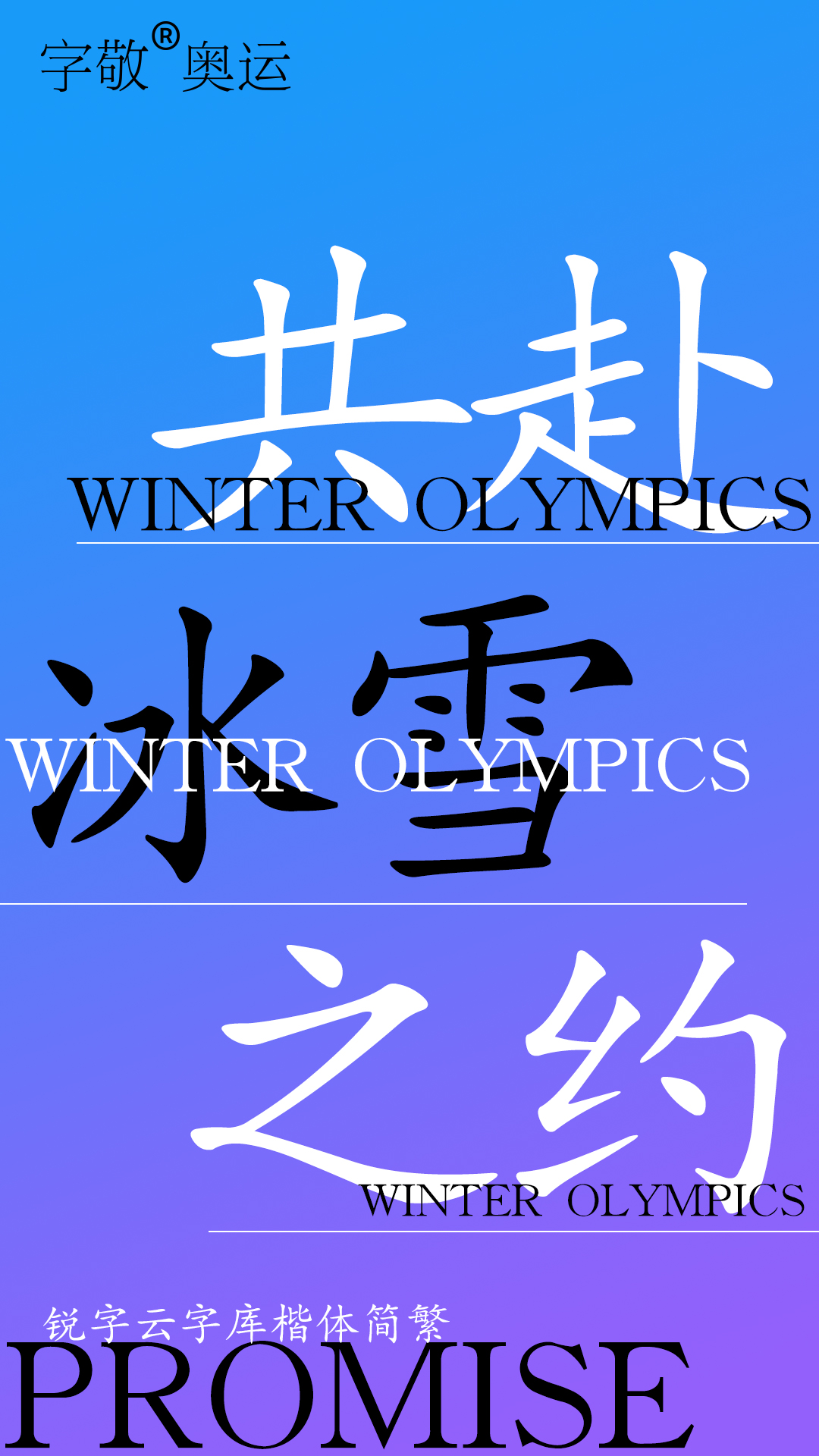
△锐字云字库楷体简繁|一款端庄的楷书经典字体,其字形较为正方,易识别、书写端正,线条粗细适中,彰显着 "和谐" 之道。
△ 潮字社国风睿楷简繁|字形流畅自然,浑厚有力,睿气十足,颇具尚强进取精神。如我们的运动员一般,不断突破新高度。
△ 潮字社凌渡鲲鹏简繁|个性的书法字体,字体笔力劲健挺拔,瘦劲精匀,愿我们的奥运健儿如鲲鹏扶摇直上,冲破云霄。
三、后记 - - 全新免费商用奥运字体即将上线
2020东京奥运会之际,我们发布了 "锐字奥运精神拼搏简免费" ,提供在奥运、亚运或体育行业、体育报道中免费商用,记录了一众经典奥运影像。
为迎接本次冬奥会,我们正在制作一款全新的奥运免费商用字体 - - 锐字奥运精神夺冠简免费,即将上线,同样提供在奥运、亚运或体育行业、体育报道中免费商用,敬请期待!